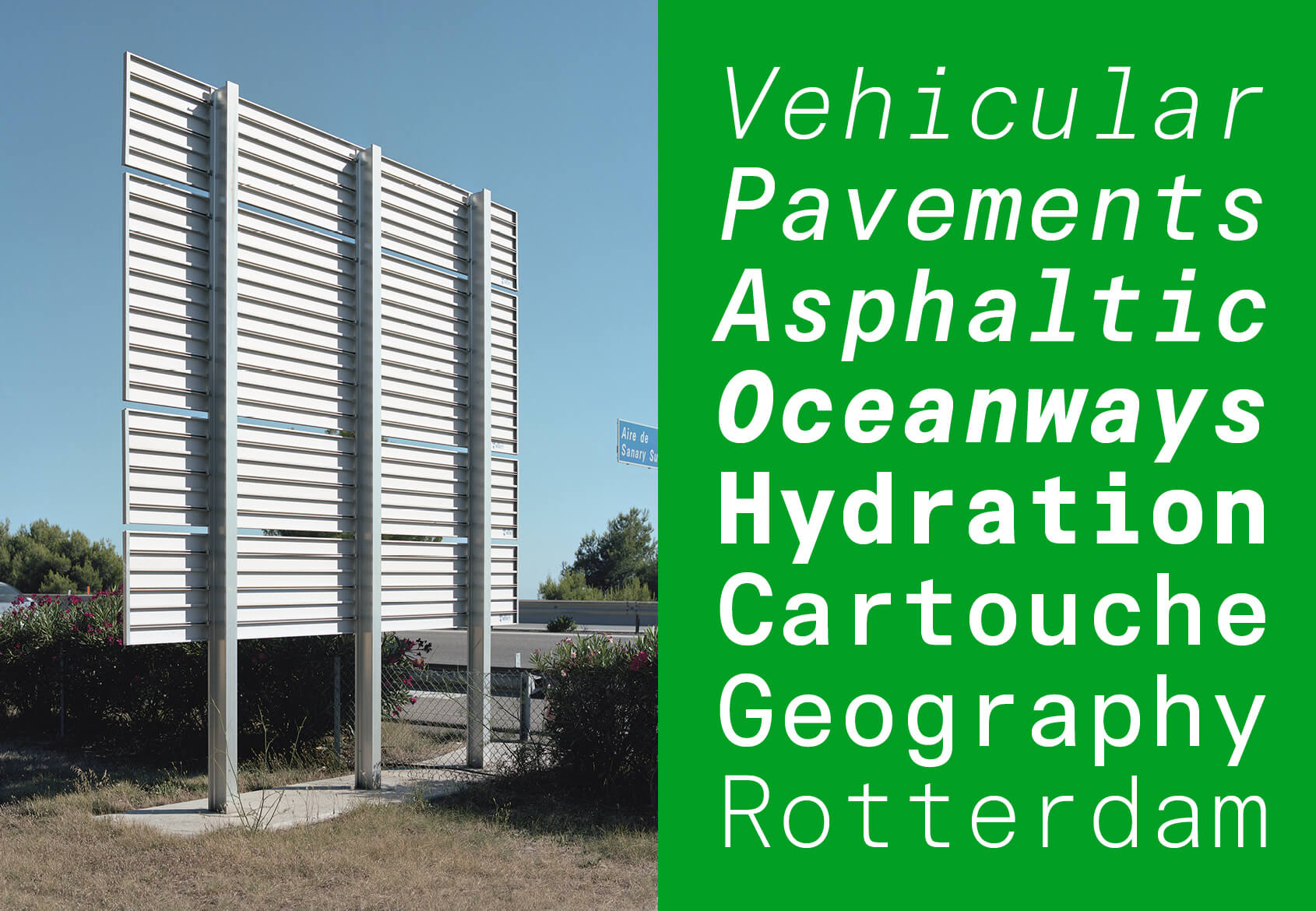
Signal Mono — моноширинная версия шрифта Signal, дополнительный голос в семействе, ещё сильнее развивающий концепцию безэмоционального, бюрократичного шрифта для серьёзных случаев.
Signal Mono — промышленный аскет, способный придать строгость любому тексту. Лучше всего он работает в инфографиках, расписаниях, нумерованных списках и других документах, где на счету каждая цифра.
Дизайн шрифта Signal опирается на шрифт Caractères, используемый на дорожных знаках по всей Франции — это значительная часть национального типографического ландшафта. Позднемодернистский образ Signal тесно увязан с административными функциями, а в пластике заметна жёсткость, характерная для большинства гротесков второй половины ХХ века. У этого шрифта есть свой голос, он даёт набору характерную типографическую краску (оцените непривычный подход к кернингу в курсивных начертаниях!).